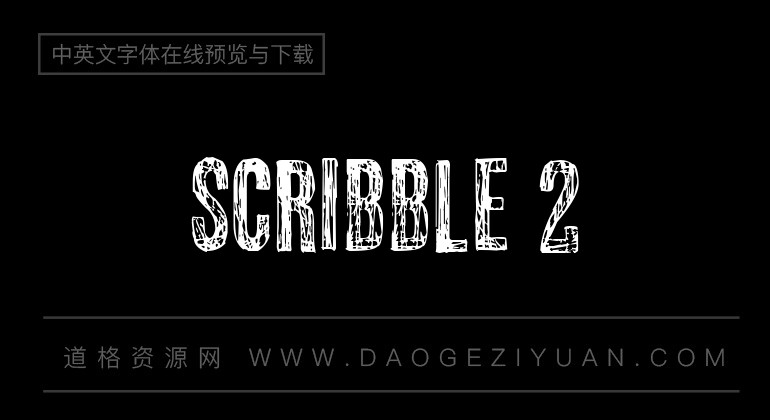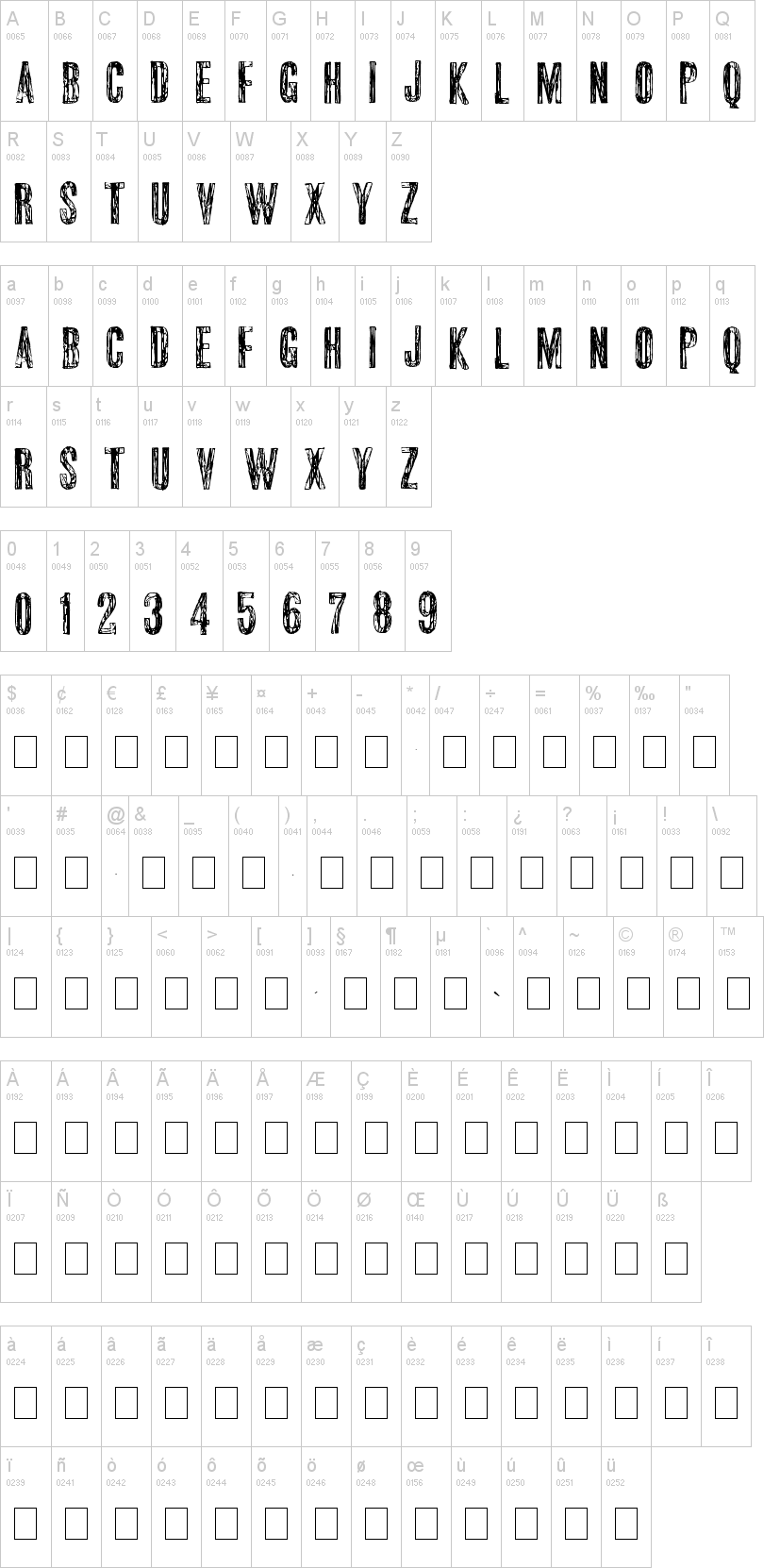
Scribble 2 字体是一种手写风格的字体,它的设计灵感来自于手写笔记和草图。这种字体的特点是线条不规则、毛边明显,看起来像是手写在纸上的效果,具有很强的个性和艺术感。 Scribble 2 字体适用于各种设计场景,比如印刷品、海报、标志和品牌设计等。它能够为设计作品带来自然、亲切、有趣的感觉,同时也可以用来突出一些重要的文字或信息。 Scribble 2 字体的字形比较多样化,包括大写字母、小写字母、数字和一些标点符号。它的字重也比较丰富,可以根据设计需要选择合适的字重来使用。 总之,Scribble 2 字体是一种富有创意和个性的字体,能够为设计作品带来不同寻常的效果,适合那些想要展现手写风格的设计师和品牌。内容介绍
Scribble 2是一款非常不错的手写艺术字体,具有很好的视觉感,适合于文化类的宣传设计、商业类品牌的广告和产品包装设计以及个性化文字排版等较多场景。